Из каких частей состоит буква: основные элементы шрифтового знака
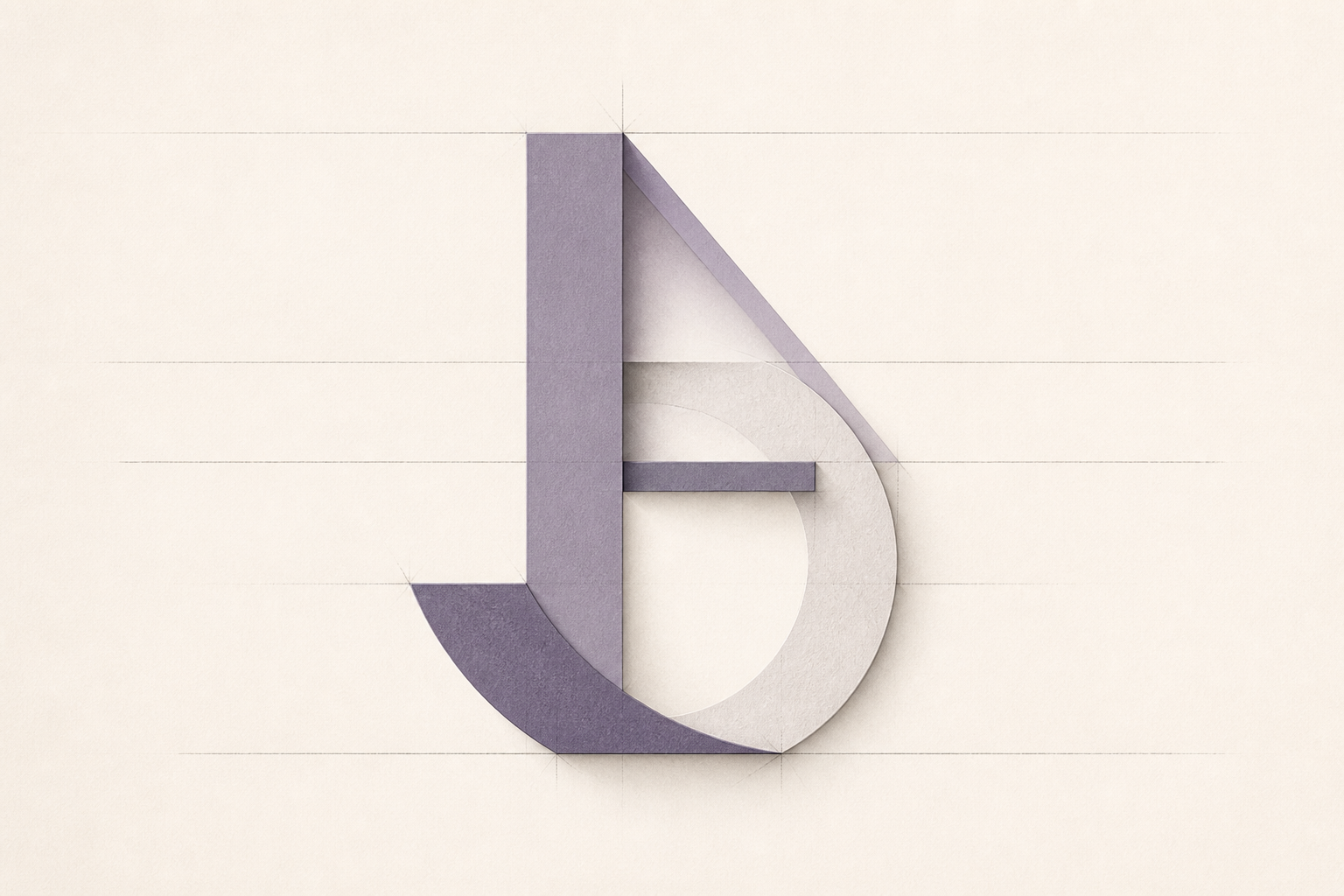
Из каких частей состоит буква: анатомия шрифтового знака
Буква состоит из конструктивных элементов, которые формируют её силуэт, внутренние просветы, положение относительно строки и характер начертания. К основным частям относятся штрихи, овал, перекладина, засечка, апертура, глазок и выносные элементы. В статье разберём терминологию, покажем примеры и объясним, как анатомия знака влияет на читаемость шрифта.
Что называют анатомией буквы
Анатомия буквы — это система названий для её видимых деталей и невидимых конструктивных ориентиров. Такой язык помогает точнее обсуждать шрифт: вместо фразы «буква выглядит тяжёлой» дизайнер может сказать, что у неё утолщённый основной штрих, маленький внутренний просвет или слишком короткая перекладина.
Важно отличать обязательные элементы от факультативных. У каждой буквы есть контур и определённое место в строке, но засечки, овал, апертура или выносной элемент встречаются только у отдельных знаков. Например, у строчной «о» есть внутренний просвет и замкнутый контур, а у «с» просвет открыт с одной стороны.
Конструктивные линии и размеры шрифта
Шрифтовой знак проектируют не изолированно, а внутри системы горизонтальных ориентиров. Они определяют высоту строчных и прописных букв, положение верхних и нижних выносных элементов, а также единый ритм строки. Даже если эти линии не напечатаны, они влияют на визуальное выравнивание текста.
- Базовая линия — воображаемая линия, на которой стоят большинство букв и знаков.
- Средняя линия — ориентир для высоты строчных букв без верхних выносных элементов.
- Высота строчных букв, или x-height, — размер основной зоны строчных знаков, например «о» или «е».
- Высота прописных букв, или cap height, — уровень верхней части большинства заглавных знаков.
- Линия верхних выносных элементов — условная граница для частей «б», «д» в некоторых конструкциях, «к» и других знаков.
- Линия нижних выносных элементов — уровень, к которому опускаются элементы «у», «р», «ф» и похожих букв.
Практический пример: если у двух шрифтов одинаковый кегль, но разная высота строчных букв, текст будет восприниматься по-разному. Шрифт с большой x-height обычно выглядит крупнее и плотнее в интерфейсе, а шрифт с меньшей x-height может казаться более воздушным и книжным.
Основные штрихи и направление конструкции
Штрих — это линия или часть контура, из которых собрана буква. Штрихи бывают вертикальными, горизонтальными, диагональными, дуговыми и криволинейными. В каллиграфических и контрастных шрифтах различают толстые и тонкие штрихи, а в гротесках толщина может быть почти одинаковой.
Основной штрих несёт главную конструктивную нагрузку знака. В «Н» это две вертикали и соединяющая их перекладина, в «А» — две диагонали и поперечный элемент, в «о» — замкнутый овальный контур. Соотношение толщины, ширины и наклона штрихов задаёт плотность и эмоциональный характер начертания.
В рукописных шрифтах направление движения пера помогает понять, почему одни участки становятся толще других. В геометрических шрифтах конструкция чаще опирается на круги, прямые и дуги. Однако механическое построение из простых фигур не гарантирует хорошего результата: оптические корректировки нужны, чтобы знаки выглядели равными по размеру и весу.
Овал, дуга, вершина и перекладина
Овал — замкнутый округлый элемент, характерный для «о», «б», «в», «ф» и многих латинских знаков. В реальном шрифте он редко является идеальной геометрической окружностью. Верх и низ овала могут быть слегка сплюснуты, а боковые части — утолщены или оптически выровнены.
Дуга соединяет прямые и кривые части буквы. Она особенно важна в «н», «м», «п», «р» и «у»: слишком резкий переход делает знак ломким, а чрезмерно мягкий — рыхлым. Вершина, или апекс, — точка соединения диагональных штрихов, например в верхней части «А», «М» или «Л».
Перекладина — горизонтальный или почти горизонтальный штрих, пересекающий другие элементы. Она есть в «А», «Н», «Е», «т» и многих других знаках. Её высота меняет образ буквы: низкая перекладина делает «А» более открытой, а высокая обычно создаёт более компактную конструкцию.
Внутренние просветы, глазок и апертура
Внутренний просвет, или counter, — пространство, ограниченное штрихами буквы. В закрытых знаках он полностью окружён контуром, как в «о», «д» или «в». В открытых знаках просвет выходит наружу, как в «с», «е» или «з». Просвет не является пустотой: он так же важен для узнавания буквы, как и чёрная форма.
Глазок — небольшой внутренний просвет или характерная внутренняя зона, которую особенно часто обсуждают применительно к «е», «а», «р» и похожим знакам. Его форма влияет на различимость букв при малом размере. Если глазок слишком мал, он может закрываться на экране или при некачественной печати.
Апертура — открытое пространство между окончаниями штрихов в незамкнутом знаке. У «с» апертура определяет степень открытости, у «е» помогает отличить букву от «о», а у «а» влияет на узнаваемость конструкции. Для интерфейсов и навигации открытые апертуры часто особенно полезны: они сохраняют различия между знаками в маленьком кегле.
Засечки, окончания и дополнительные детали
Засечка — короткий элемент на конце основного штриха. Она характерна для антиквенных шрифтов, но её форма может быть прямоугольной, клиновидной, волосной или плавно соединённой со штрихом. Засечки влияют на ритм строки, распределение чёрного и белого и общее ощущение текста.
Термин «окончание» шире: он обозначает финальную часть штриха независимо от того, есть ли у неё засечка. Окончание может быть срезанным, округлым, каплевидным, наклонным или декоративным. В гротесках выразительность часто создаётся именно формой окончаний, контрастом толщины и направлением среза.
К другим дополнительным деталям относят шип, или spur, — небольшой выступ у соединения штрихов, ушко, или ear, — выступающую часть некоторых строчных букв, а также хвост, или tail, — удлинённый элемент в нижней или боковой части знака. Эти термины применимы не ко всем гарнитурам и зависят от конкретной конструкции.
Замкнутые и открытые формы: почему это важно
Замкнутая форма полностью окружает внутренний просвет, а открытая оставляет в контуре разрыв. Различие заметно в парах «о» и «с», «в» и «з», а также в разных вариантах строчной «а». Открытость, размер просвета и характер соединений определяют, насколько быстро читатель распознаёт знак.
При разработке шрифта полезно проверять не отдельную букву, а соседство похожих знаков. Например, слишком закрытая «с» может начать напоминать «о», а маленький просвет в «е» — исчезнуть в плотном тексте. Поэтому дизайнер сравнивает не только контуры, но и белые промежутки между буквами.
Как элементы буквы влияют на читаемость
Читаемость зависит от согласованности нескольких параметров: формы знаков, размера внутренних просветов, различимости похожих букв, толщины штрихов, межбуквенного расстояния и высоты строчных символов. Один выразительный элемент не компенсирует слабую систему. Даже красивый логотипный шрифт может быть неудобен для длинного текста, если его просветы слишком малы.
- Увеличивайте просветы, если текст должен хорошо читаться на экране и в небольшом размере.
- Проверяйте пары «п» и «т», «и» и «й», «ш» и «щ», «о» и «с», чтобы отличия сохранялись в реальном наборе.
- Согласовывайте толщину вертикальных и горизонтальных штрихов с общей логикой начертания.
- Контролируйте высоту выносных элементов, чтобы строки не выглядели случайно разреженными.
- Оценивайте буквы в словах, а не только на увеличенном макете.
Практический разбор: из чего собраны буквы «А», «а» и «ж»
Заглавная «А» обычно строится из двух диагональных штрихов и перекладины. В месте их соединения образуется вершина, а по бокам остаются внешние просветы. В шрифте с засечками к концам диагоналей добавляются опорные элементы. Высота перекладины, ширина знака и угол наклона определяют его устойчивость и открытость.
Строчная «а» может иметь двухэтажную или одноэтажную конструкцию. В двухэтажной форме видны овал, правый вертикальный штрих, верхний элемент и внутренний просвет; в одноэтажной форма ближе к округлому знаку с хвостом или соединительным штрихом. Выбор конструкции заметно меняет характер гарнитуры и её пригодность для разных задач.
Буква «ж» показывает, как несколько диагональных штрихов объединяются вокруг центральной оси. В ней важны пересечения, боковые просветы, симметрия и баланс веса. Если центральная часть слишком плотная, знак становится похожим на тёмное пятно; если боковые элементы чрезмерно раздвинуты, буква распадается и нарушает ритм слова.
Чем отличается терминология кириллицы и латиницы
Большинство терминов анатомии буквы применимо и к кириллице, и к латинице: штрих, овал, просвет, апертура, засечка, перекладина и выносной элемент описывают общие принципы. При этом конкретные формы знаков различаются. Нельзя автоматически переносить конструкцию латинской «a» на кириллическую «а» или считать их взаимозаменяемыми.
Кириллический набор требует отдельной проверки характерных знаков: «д», «л», «ж», «ф», «ч», «щ», «ы» и «й». Их пропорции, соединения и выносные элементы должны поддерживать общий стиль шрифта, но не обязаны копировать решения латинской части. Гарнитура выглядит цельной, когда обе письменные системы имеют сопоставимый ритм и визуальный вес.
Частые ошибки при анализе и создании букв
Ошибки возникают, когда дизайнер оценивает только внешний контур и игнорирует внутренние пространства, соседние знаки и назначение шрифта. Для крупного заголовка допустимы необычные окончания или контрастные детали, но в интерфейсе, подписи или основном тексте приоритетом остаются узнаваемость и стабильный ритм.
- Копируют геометрию без оптических поправок и получают разные по восприятию круги и прямоугольники.
- Уменьшают внутренние просветы, из-за чего буквы сливаются в плотном наборе.
- Делают все штрихи одинаковыми, хотя выбранная стилистика предполагает контраст толщины.
- Забывают о выносных элементах и получают строки с конфликтующими интервалами.
- Проверяют только заглавные буквы, но не тестируют строчные, цифры и знаки препинания.
- Используют декоративные детали в тексте, где нужна нейтральная и быстрая навигация.
Чеклист проверки шрифтового знака
Перед выпуском буквы в состав гарнитуры оцените её в трёх масштабах: крупном, рабочем и маленьком. Крупный масштаб помогает увидеть качество кривых и соединений, рабочий показывает характер слова, а маленький выявляет закрывающиеся просветы и слабые различия между похожими знаками.
- Определите базовую линию, высоту строчных и прописных знаков.
- Проверьте толщину основных и соединительных штрихов.
- Сравните внешние и внутренние просветы с соседними буквами.
- Убедитесь, что апертура остаётся открытой в целевом размере.
- Проверьте вершины, дуги и окончания на плавность и согласованность.
- Соберите несколько слов и оцените ритм, плотность и читаемость.
- Протестируйте знак в нужном контексте: текст, логотип, интерфейс или плакат.
Как применять анатомию буквы при создании шрифта
Начинайте не с украшений, а с базовой системы: определите высоту строчных, пропорции прописных, диапазон толщины и общий характер штрихов. Затем создайте несколько опорных знаков, например «н», «о», «п» и «а». На их основе легче выстроить остальные буквы, потому что они показывают вертикали, кривые, просветы и типичные соединения.
После построения основных форм переходите к оптической настройке. Круглые знаки часто немного выходят за базовую и верхнюю линии, чтобы визуально казаться равными плоским буквам. Диагональные штрихи и острые вершины также требуют корректировки веса и расстояний. Эти небольшие изменения делают строку ровной не математически, а зрительно.
Финальный этап — проверка набора. Отдельная буква может выглядеть убедительно, но в слове проявятся слишком тесные пары, провалы в ритме или конфликтующие формы. Используйте короткие тестовые фразы с повторяющимися и похожими знаками, а затем оцените шрифт в тех размерах и носителях, для которых он создаётся.
Что такое анатомия буквы простыми словами?
Анатомия буквы — это названия её частей и принципов построения. К ним относятся штрихи, овал, просвет, перекладина, засечка, апертура, вершина, хвост и выносные элементы. Терминология помогает описывать форму знака точно и одинаково для дизайнера, редактора и типографа.
Что такое базовая линия в шрифте?
Базовая линия — воображаемый горизонтальный ориентир, на котором располагается основная часть букв. Большинство строчных и прописных знаков визуально опираются на неё, а элементы вроде нижних выносных частей опускаются ниже. Базовая линия помогает согласовать положение символов в одной строке.
Чем просвет отличается от апертуры?
Просвет — это внутреннее пространство внутри или между штрихами буквы. Он может быть полностью замкнутым или открытым. Апертура — конкретный открытый участок контура, через который просвет соединяется с внешним пространством. Поэтому апертура является одним из типов конструктивного решения просвета.
Зачем буквам нужны засечки?
Засечки завершают основные штрихи и влияют на ритм, пропорции и характер шрифта. Они могут помогать визуально связывать буквы в строку, но не являются обязательным условием хорошей читаемости. Шрифт без засечек также может быть удобным, если его формы, интервалы и просветы согласованы.
Почему одинаковые по размеру буквы выглядят неодинаково?
Глаз воспринимает круглые и острые формы иначе, чем плоские. Поэтому овал обычно немного выходит за условные границы строки, а вершины диагональных букв могут требовать дополнительного пространства. Такие оптические компенсации помогают буквам казаться равными по высоте и весу, хотя их геометрические размеры различаются.
Какие элементы особенно важны для кириллического шрифта?
Для кириллицы особенно важно проверить конструкцию «д», «ж», «ф», «ч», «щ», «ы» и «й». У этих знаков есть характерные соединения, выносные элементы или дополнительные штрихи, которые сильно влияют на узнаваемость набора. Их следует согласовывать с латинской частью, но не копировать механически.
Можно ли создать шрифт, зная только названия частей букв?
Одной терминологии недостаточно, но она даёт прочную основу для работы. Создателю шрифта нужно дополнительно понимать пропорции, интервалы, контраст штрихов, формат файла и особенности применения. Практика начинается с анализа существующих гарнитур, построения опорных знаков и регулярной проверки текста в реальном размере.
Буква — это не просто контур, а система штрихов, просветов, окончаний и конструктивных линий. Понимание анатомии шрифтового знака помогает точнее выбирать гарнитуры, находить причины плохой читаемости и создавать цельные наборы символов. Начните с опорных форм, проверьте их в словах и только потом добавляйте декоративные особенности.